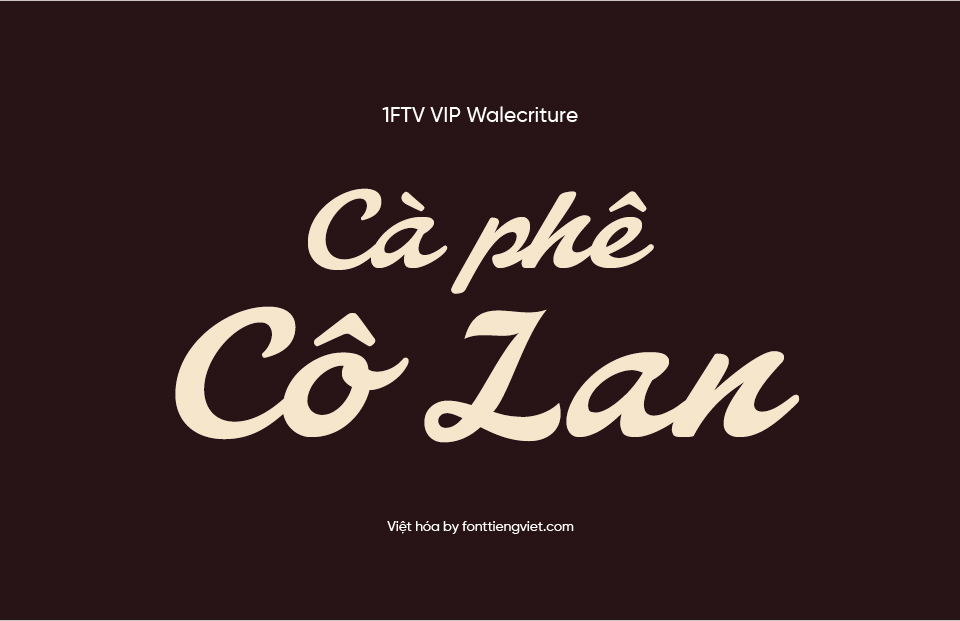
Giới thiệu về bộ Font Việt hóa 1FTV VIP Walecriture
Trong thế giới đồ họa hiện đại, việc lựa chọn một Font Chữ phù hợp đóng vai trò then chốt tạo nên linh hồn cho tác phẩm. Font Việt hóa 1FTV VIP Walecriture là một trong những bộ font Script nghệ thuật đang được cộng đồng thiết kế tại Việt Nam săn đón. Với đường nét uyển chuyển, mềm mại nhưng không kém phần sang trọng, bộ font này mang đến một hơi thở mới cho các sản phẩm truyền thông số. Đặc biệt, phiên bản 1FTV VIP Walecriture đã được tối ưu hóa đầy đủ dấu tiếng Việt, giúp người dùng không còn lo lắng về lỗi hiển thị khi soạn thảo văn bản hay làm layout chuyên nghiệp.
Tại sao nên sử dụng Font Việt hóa 1FTV VIP Walecriture?
Điểm mạnh nhất của Font Việt hóa 1FTV VIP Walecriture chính là sự linh hoạt trong ứng dụng thực tế. Từ thiết kế thiệp mời, bìa sách, menu nhà hàng đến các banner quảng cáo trên mạng xã hội, font chữ này đều thể hiện được phong cách tinh tế và đẳng cấp. Các ký tự được chăm chút tỉ mỉ với độ tương phản hợp lý, đảm bảo khả năng đọc tốt trên cả màn hình điện thoại và bản in ấn. Ngoài ra, tính năng tương thích tốt với các phần mềm đồ họa phổ biến như Photoshop, Illustrator hay Canva khiến nó trở thành công cụ hỗ trợ đắc lực cho cả những người mới bắt đầu học thiết kế.
Kết luận về bộ font nghệ thuật này
Sở hữu Font Việt hóa 1FTV VIP Walecriture trong bộ sưu tập cá nhân sẽ giúp bạn nâng tầm giá trị cho mọi dự án sáng tạo. Đây là giải pháp hoàn hảo để tạo nên những tác phẩm độc bản và thu hút thị giác người xem ngay từ cái nhìn đầu tiên. Đừng bỏ lỡ cơ hội tải về và trải nghiệm Font Miễn Phí, Font Việt Hóa, Font Việt hóa 1FTV VIP Walecriture để khám phá sức mạnh của nghệ thuật chữ viết trong việc truyền tải thông điệp cảm xúc một cách trọn vẹn nhất.